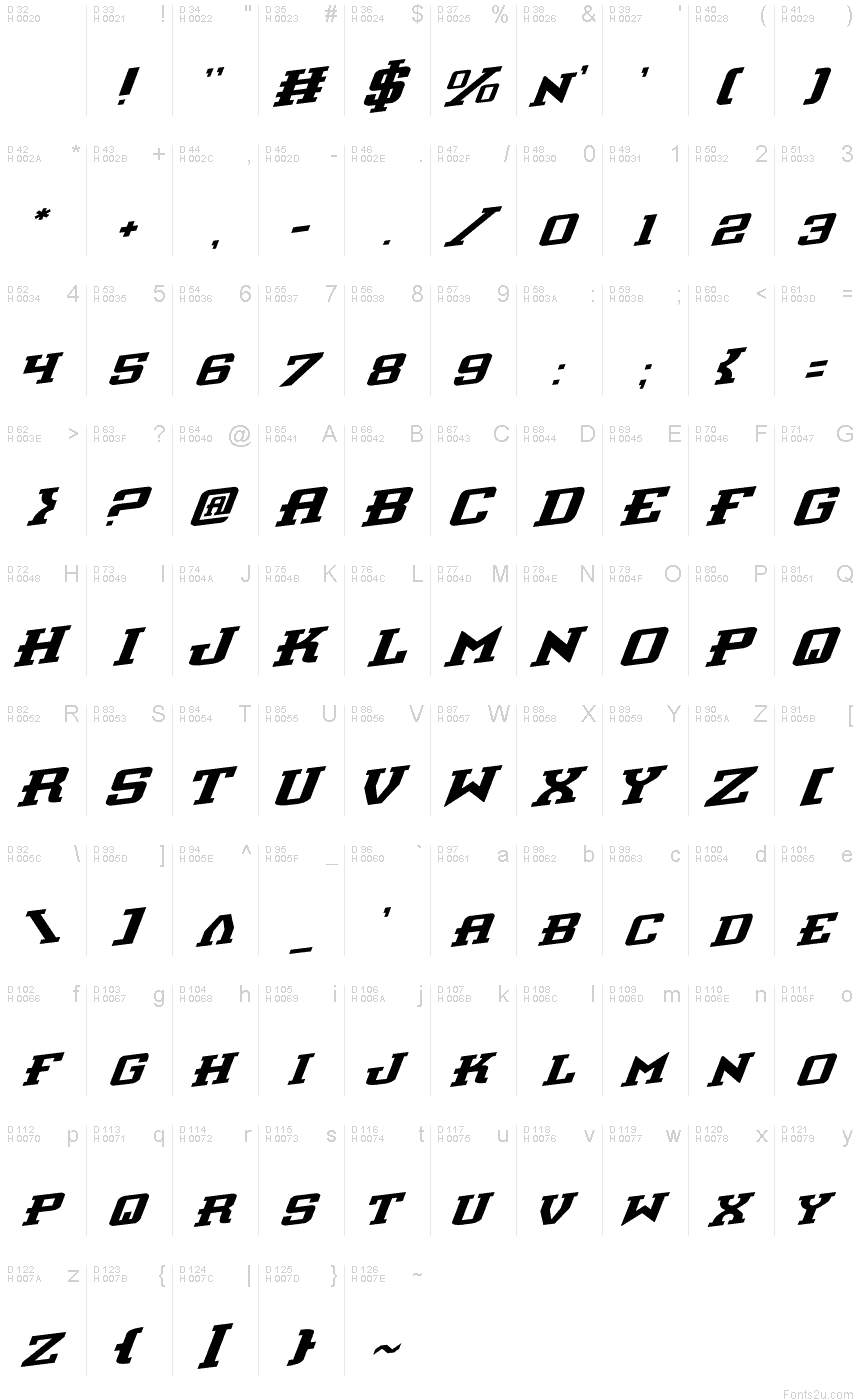
Interceptor Rotalic von Iconian Fonts ist eine kostenlose, futuristische Sports-Display-Schrift. Ihre scharf geneigten Großbuchstaben und eingekerbten Ecken verleihen den Lettern einen rasanten, gepanzerten Look. Durch die breiten, keilartigen Serifen und kantigen Einkerbungen wirkt die Schrift aggressiv und mechanisch – fast wie für Motion Graphics entworfen, statt wie ein neutraler Display-Font.
Sie eignet sich perfekt für Gaming-Logos, Action-Filmtitel, Plakatüberschriften, Esports-Branding und technologisch orientierte Headlines, bei denen es auf diesen treibenden, durchsetzungsstarken Neigungseffekt ankommt. Als Free-Font eignet sie sich zudem hervorragend für Monogramme oder Initialen, da die Großbuchstaben genug Charakter und Ausdruck besitzen, um auch in kurzen Wortfolgen sofort aufzufallen.